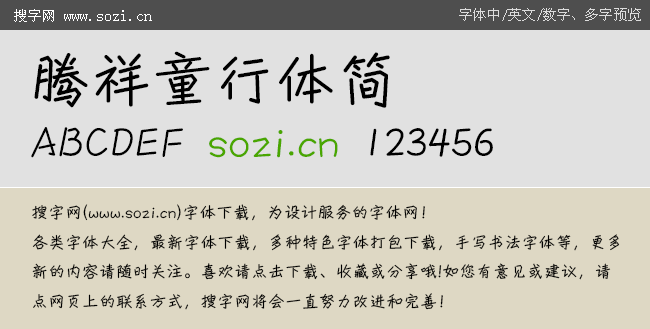
騰祥童行體簡
搜字網(wǎng)提供一款騰祥童行體簡中文藝術(shù)字體下載,騰祥童行體是一款字跡活潑秀氣的兒童行書字體,字里行間流露著孩子的稚趣和童真,給人流暢整潔的美感,字跡穩(wěn)重而不輕浮?捎糜谟∷⒊霭妗b設(shè)計(jì)、廣告設(shè)計(jì)、網(wǎng)頁設(shè)計(jì)等。